Chào các bạn, đây là dự án tự làm của mình, tuy là chưa đến 200 nhưng mình nghĩ có một ngày xa xôi nào đó sẽ có, mà sắp tới mình khá bận nên quyết định share trước, coi như share đậu đại học =)))))) nói share 200 follows cho sang vậy hoi =))) chứ cũng bình thường à, mấu chốt là có font mình tự việt hóa. Mình đã cố gắng làm demo đẹp mà nó vẫn xấu =)) thau các bạn nhắm mắt cho qua nhé <3
Rồi tiếp theo, dưới đây là những font mình muốn share, tổng cộng là 6. Đúng không nhiều nhưng nó có font mình tự việt hóa nên mình thấy 6 là khá nhiều rồi. Nào xuống xem demo nào nào ~~
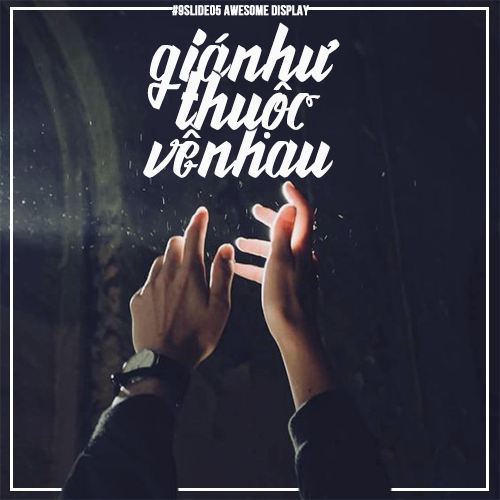
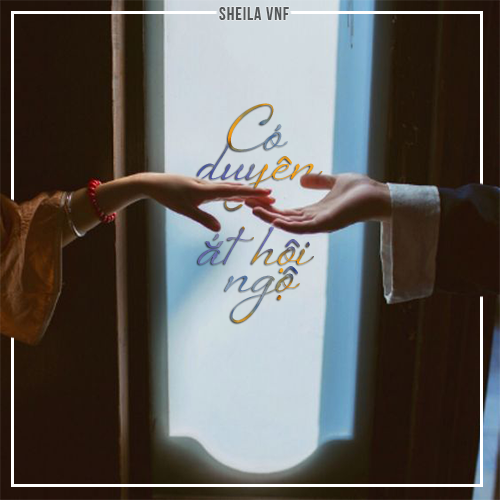
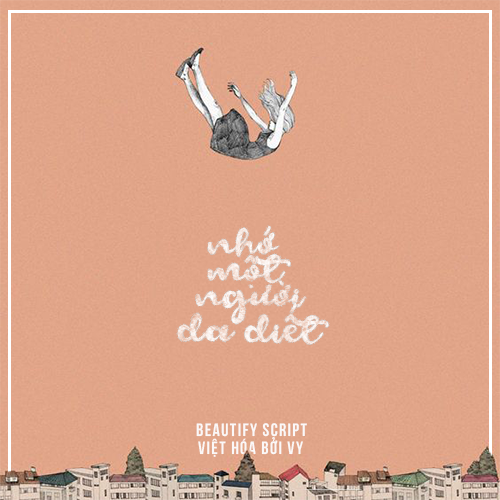
(font tự việt hóa, tuy không chuyên nghiệp nhưng đã cố gắng hết sức)
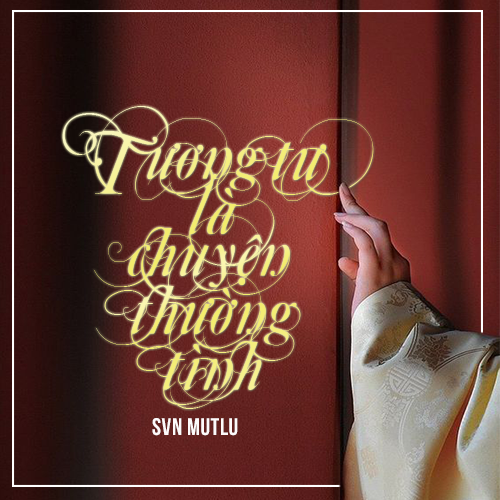
(best font =)))) cái này là font nó có sẵn mấy cái tua ấy)
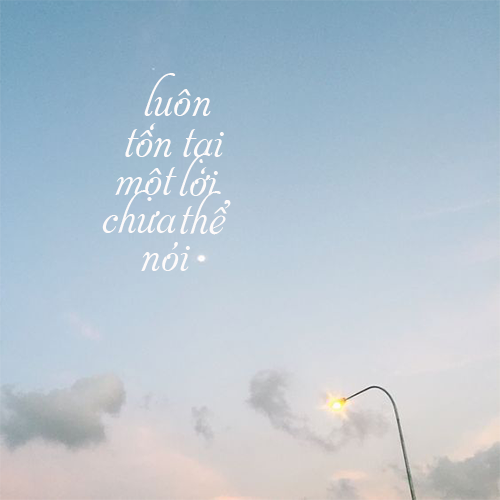
(quên ghi tên font này, UVF Aphrodite Pro)